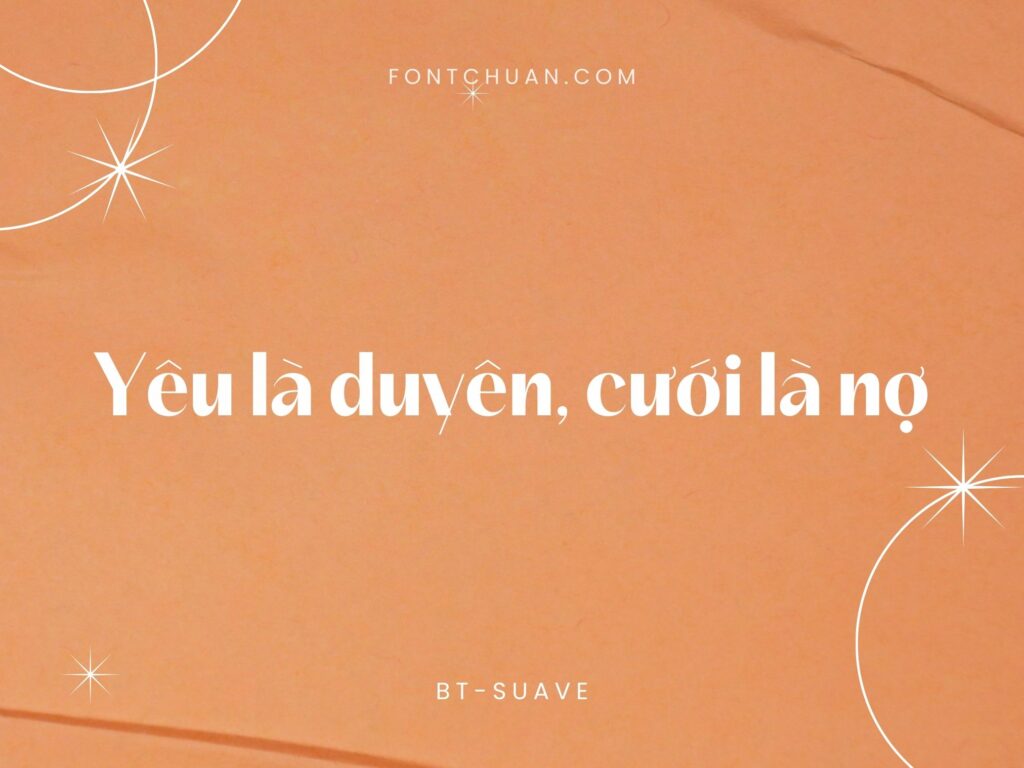
Font Bt Suave Trọn Bộ Font Tiếng Việt
BT Suave là một font chữ hiển thị độc đáo được thiết kế bởi BeauType Studio, nhằm tạo ra cảm giác nhẹ nhàng, tinh tế và uyển chuyển trong thiết kế. Font này kết hợp giữa hình thức hiện đại và các đường nét tương phản cao, với sự chú ý đến từng chi tiết, giúp tích hợp hoàn hảo vào việc xây dựng thương hiệu cho các dự án thiết kế cao cấp. BT Suave bao gồm 20 kiểu chữ khác nhau về độ dày và độ nghiêng, đáp ứng nhu cầu phân cấp phức tạp khi ứng dụng trong các dự án đồ họa. Font hỗ trợ đầy đủ tiếng Việt và nhiều ngôn ngữ khác, được sưu tầm và đăng bởi thành viên của Font Chuẩn.
Với thiết kế thanh lịch, mềm mại và độ tương phản cao, BT Suave là lựa chọn lý tưởng làm Font chữ spa, giúp các thương hiệu chăm sóc sức khỏe, làm đẹp và spa thể hiện sự tinh tế, sang trọng và chuyên nghiệp trong từng sản phẩm thiết kế. Font này cũng phù hợp cho logo, tiêu đề, poster và các ấn phẩm truyền thông cần sự hiện đại và tinh tế. Nhờ sự linh hoạt và đa dụng, BT Suave còn được ứng dụng hiệu quả trong các ngành quảng cáo, thiệp cưới, giáo dục, cũng như các sự kiện đặc biệt như lễ hội, sinh nhật, ngày Nhà giáo và Valentine.